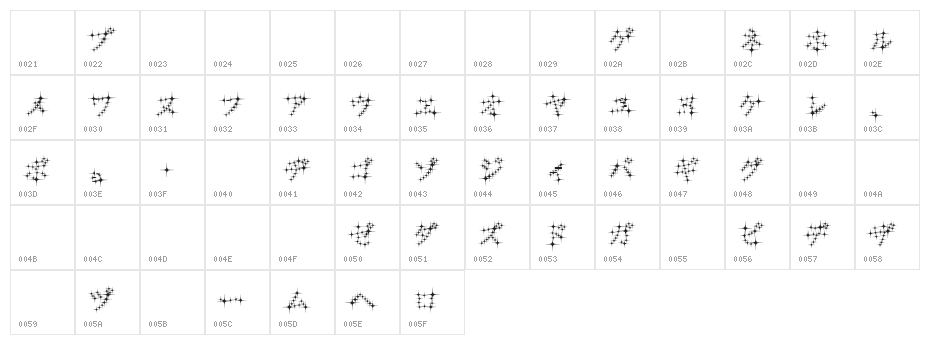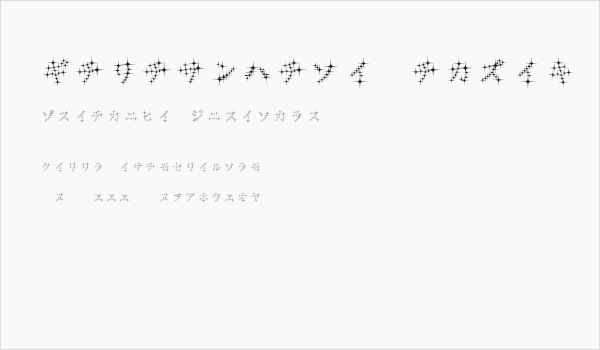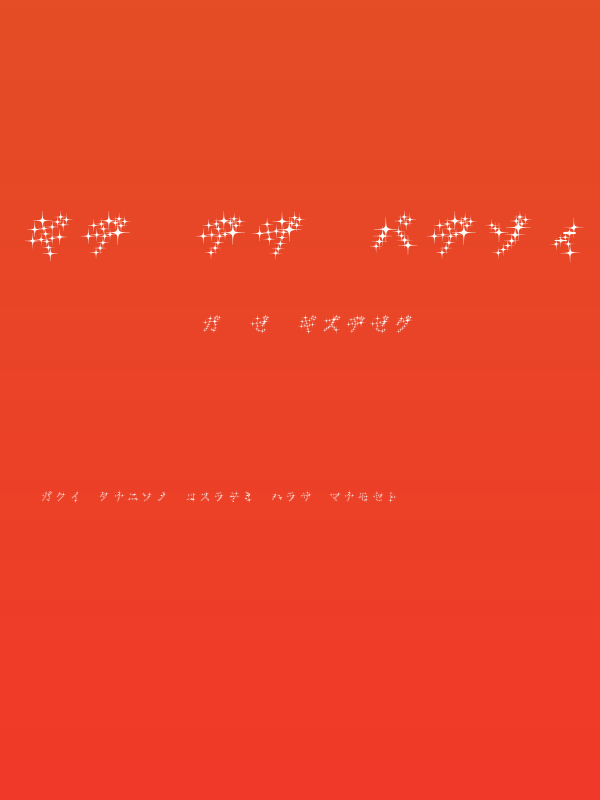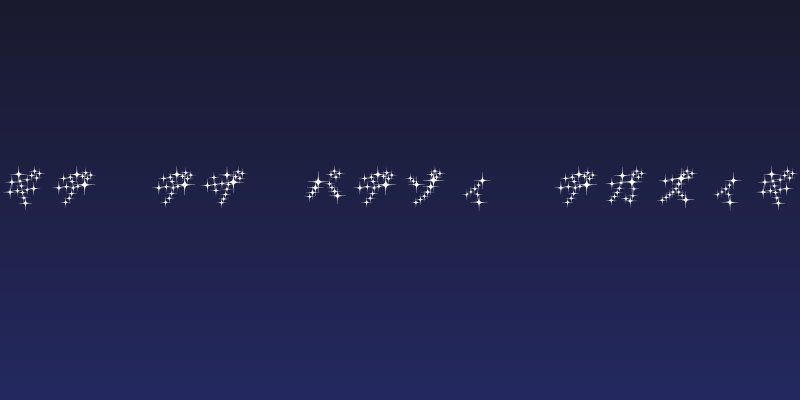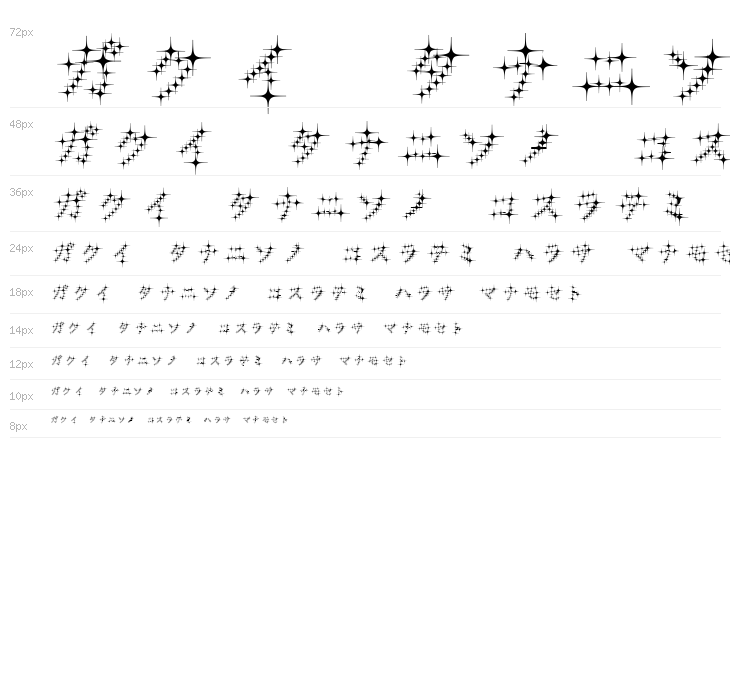
GalaxyfaceKatReg Font
| Progetti proposti | Ideal for fantasy-themed posters, children's book covers, party invitations, or any project needing a magical touch. |